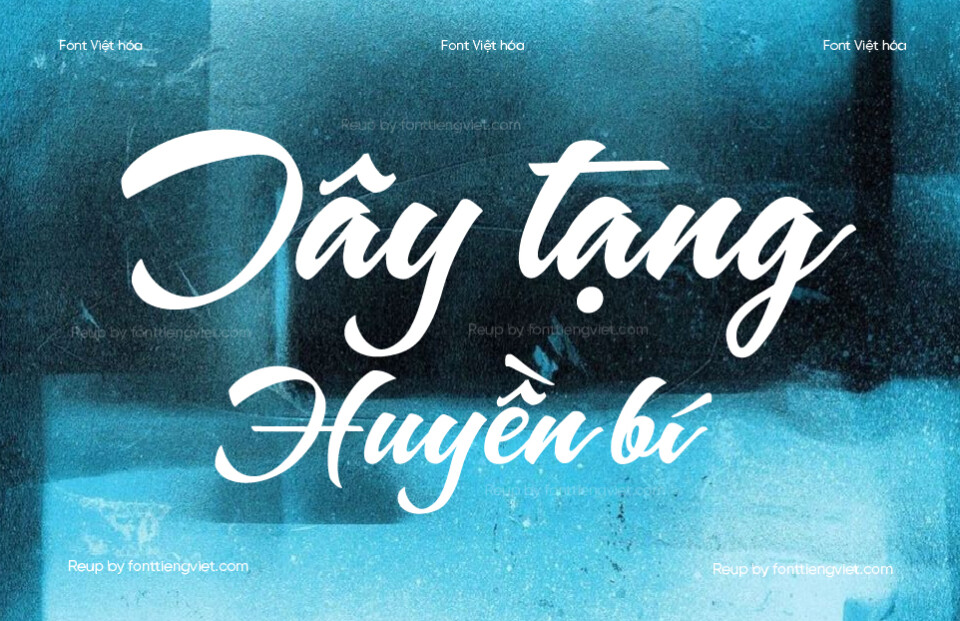
Trong thế giới thiết kế đồ họa ngày nay, việc lựa chọn một Font Chữ phù hợp có thể tạo nên sự khác biệt lớn cho bất kỳ dự án nào. Và khi nhắc đến những lựa chọn độc đáo, phong cách và tối ưu cho tiếng Việt, không thể không kể đến Font Việt hóa UTM A&S Snapper. Đây không chỉ là một font chữ thông thường mà còn là một công cụ mạnh mẽ giúp các nhà thiết kế thể hiện sự sáng tạo và chuyên nghiệp. Với những đường nét riêng biệt và khả năng hỗ trợ tiếng Việt hoàn hảo, UTM A&S Snapper đã nhanh chóng chiếm được cảm tình của cộng đồng thiết kế, từ những người mới bắt đầu cho đến các chuyên gia lão luyện. Bài viết này sẽ đi sâu khám phá mọi khía cạnh của font chữ đặc biệt này, từ đặc điểm nổi bật đến những ứng dụng thực tiễn trong các dự án thiết kế.
Giới Thiệu Chung về Font Việt hóa UTM A&S Snapper
Font Việt hóa UTM A&S Snapper là một trong những thành viên nổi bật của bộ sưu tập font UTM Việt hóa, được biết đến với chất lượng cao và khả năng hỗ trợ đầy đủ bảng mã tiếng Việt. Được thiết kế với phong cách hiện đại nhưng vẫn giữ được nét độc đáo riêng, UTM A&S Snapper mang đến một làn gió mới cho ngành typography. Ban đầu, font chữ này có thể xuất phát từ một thiết kế nước ngoài, nhưng qua quá trình Việt hóa kỹ lưỡng, nó đã được bổ sung đầy đủ các dấu và ký tự đặc trưng của tiếng Việt, đảm bảo tính thẩm mỹ và khả năng đọc tuyệt vời cho người dùng Việt Nam. Sự ra đời của các font Việt hóa như UTM A&S Snapper đã giúp giải quyết vấn đề lớn về hiển thị chữ tiếng Việt, vốn thường gặp phải lỗi font hoặc hiển thị không đẹp mắt với các font quốc tế chưa được tối ưu.
Font chữ này được ưa chuộng bởi sự linh hoạt và khả năng thích ứng cao với nhiều loại hình thiết kế khác nhau. Từ những dự án mang tính cá nhân nhỏ lẻ cho đến các chiến dịch truyền thông quy mô lớn, UTM A&S Snapper đều có thể phát huy tối đa hiệu quả. Việc sử dụng một font chữ được Việt hóa chuẩn mực không chỉ giúp tăng tính chuyên nghiệp cho tác phẩm mà còn thể hiện sự tôn trọng đối với ngôn ngữ và văn hóa Việt Nam.
Đặc Điểm Nổi Bật Của UTM A&S Snapper
UTM A&S Snapper nổi bật với một số đặc điểm chính khiến nó trở thành lựa chọn hàng đầu cho nhiều nhà thiết kế:
- Phong Cách Thiết Kế Độc Đáo: Font sở hữu những đường nét mạnh mẽ nhưng không kém phần tinh tế, mang lại cảm giác hiện đại và năng động. Nó có thể được xem là một sự kết hợp hài hòa giữa sự cứng cáp và mềm mại, tạo nên một vẻ ngoài rất riêng biệt.
- Khả Năng Đọc Tốt: Mặc dù có phong cách độc đáo, UTM A&S Snapper vẫn đảm bảo khả năng đọc tốt, ngay cả ở kích thước nhỏ. Điều này rất quan trọng đối với các ấn phẩm in ấn hoặc các giao diện người dùng.
- Hỗ Trợ Tiếng Việt Hoàn Hảo: Đây là yếu tố then chốt. Việc font được Việt hóa kỹ lưỡng giúp hiển thị tất cả các dấu và ký tự tiếng Việt một cách chính xác và đẹp mắt, tránh các lỗi như vỡ dấu, sai vị trí dấu hoặc khoảng cách chữ không đều.
- Tính Linh Hoạt Cao: Font có thể được sử dụng trong nhiều ngữ cảnh khác nhau, từ tiêu đề ấn tượng đến nội dung chính cần sự rõ ràng.
Ứng Dụng Đa Dạng Của Font Việt hóa UTM A&S Snapper Trong Thiết Kế
Với những ưu điểm vượt trội, Font Việt hóa UTM A&S Snapper có thể được ứng dụng rộng rãi trong nhiều lĩnh vực thiết kế khác nhau. Dưới đây là một số ví dụ điển hình:
- Thiết Kế Logo và Nhận Diện Thương Hiệu: Với phong cách mạnh mẽ nhưng vẫn độc đáo, font này rất phù hợp để tạo ra những logo có cá tính riêng, giúp thương hiệu dễ dàng gây ấn tượng với khách hàng.
- Thiết Kế Poster, Banner, Tờ Rơi: UTM A&S Snapper làm cho các tiêu đề và thông điệp trên poster trở nên nổi bật, thu hút sự chú ý của người xem.
- Thiết Kế Website và Giao Diện Người Dùng (UI/UX): Font có thể được dùng cho các tiêu đề hoặc các phần nhấn mạnh trên website, mang lại vẻ ngoài hiện đại và chuyên nghiệp.
- Thiết Kế Sách, Tạp Chí, Báo Chí: Đối với các tiêu đề chương, mục lục hoặc các phần giới thiệu đặc biệt, UTM A&S Snapper có thể tạo điểm nhấn ấn tượng.
- Thiết Kế Ấn Phẩm Cá Nhân: Từ thiệp mời, thiệp chúc mừng đến các dự án nghệ thuật cá nhân, font này đều có thể thêm vào nét sáng tạo và độc đáo.
Tại Sao Font Việt hóa Lại Quan Trọng?
Việc sử dụng font Việt hóa không chỉ là một lựa chọn mà còn là một yêu cầu quan trọng trong nhiều dự án thiết kế tại Việt Nam. Nó đảm bảo rằng nội dung tiếng Việt được hiển thị một cách chính xác, chuyên nghiệp và có tính thẩm mỹ cao. Một font chưa được Việt hóa hoặc Việt hóa không chuẩn có thể dẫn đến các lỗi hiển thị như thiếu dấu, dấu sai vị trí, hoặc khoảng cách giữa các chữ bị lệch lạc, làm giảm chất lượng tổng thể của thiết kế và gây khó chịu cho người đọc. Đặc biệt trong môi trường giáo dục, việc sử dụng font Việt hóa chuẩn xác là điều cần thiết để đảm bảo thông tin được truyền tải rõ ràng và chính xác.
Khi sử dụng, hãy cân nhắc ngữ cảnh và mục đích thiết kế để chọn kích thước, màu sắc và sự kết hợp với các font khác sao cho hợp lý, nhằm tối ưu hóa hiệu quả thị giác và truyền tải thông điệp một cách rõ ràng nhất.
Tổng kết lại, Font Việt hóa UTM A&S Snapper là một tài nguyên quý giá cho bất kỳ nhà thiết kế nào đang tìm kiếm sự độc đáo và chuyên nghiệp cho các dự án của mình. Với khả năng hỗ trợ tiếng Việt hoàn hảo và phong cách thiết kế ấn tượng, font này chắc chắn sẽ giúp bạn nâng tầm tác phẩm của mình. Việc lựa chọn một Font Chữ Việt hóa chuẩn mực như UTM A&S Snapper không chỉ đảm bảo tính thẩm mỹ mà còn thể hiện sự tôn trọng đối với ngôn ngữ mẹ đẻ. Đừng ngần ngại khám phá và ứng dụng font chữ tuyệt vời này để tạo nên những sản phẩm thiết kế đầy ấn tượng và thu hút.